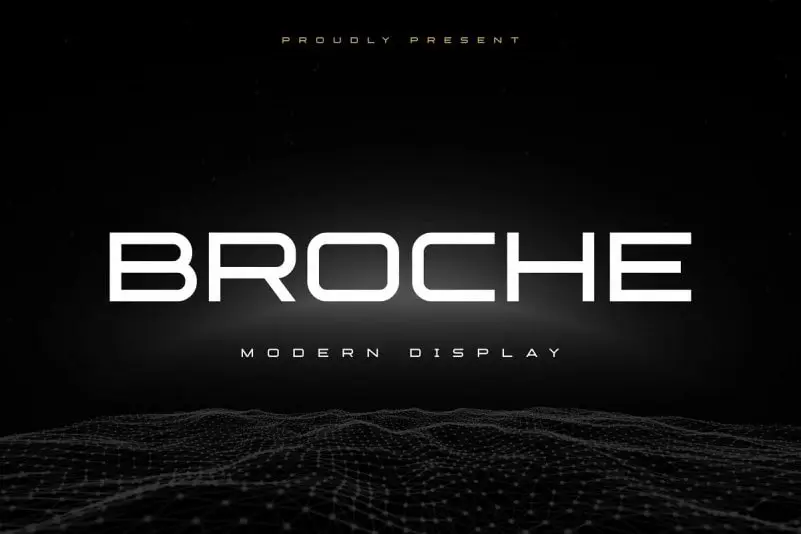
Broche Font
A Broche Font é uma elegante serif que desperta a imaginação com sua disposição futurista e moderna. Suas linhas suaves e detalhes meticulosamente criados proporcionam um ar sofisticado ao design, ideal para aplicação em variados ambientes. Seu charme clássico se combina perfeitamente com o estilo futurista, tornando-a uma escolha inteligente tanto para uso em logotipos e rótulos de embalagens quanto para criação de materiais de marketing que requerem um visual único e memorável. Seja para cartazes impactantes ou camisetas ousadas, a Broche Font tem o poder de transformar qualquer projeto gráfico em destaque. E se você está procurando por uma fonte serif que combine elegância com modernidade na medida certa? Esta é a escolha perfeita.